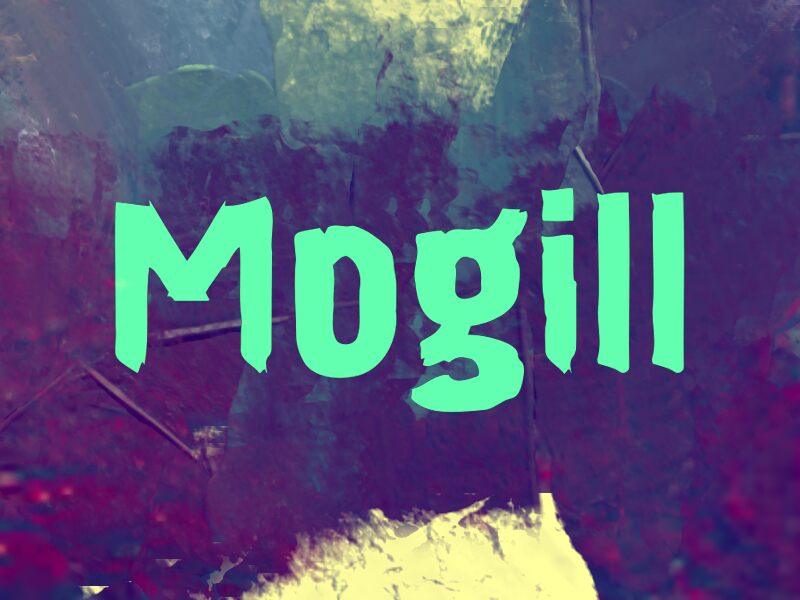
Mogill от Wep — это бесплатный брутальный кистевой шрифт с легким налетом готики. Буквы выглядят так, будто их нарисовали сухой, обильно нагруженной краской кистью: они тяжелые, прямые и с немного рваными краями. Благодаря этому шрифт воспринимается скорее как рукописное леттеринг-решение, чем как аккуратная цифровая гарнитура.
Он идеально подходит для заголовков на плакатах, обложек альбомов, названий фильмов ужасов, айдентики пабов и флаеров мероприятий — везде, где нужен бесплатный шрифт с характером, но без ухода в чистое средневековье. Также он хорош для коротких надписей на упаковке и начала глав: массивные формы и «рваные» концы кисти придают даже паре букв уверенный, крафтовый вид.
Mogill
Презентация и наглядный образец шрифта Mogill